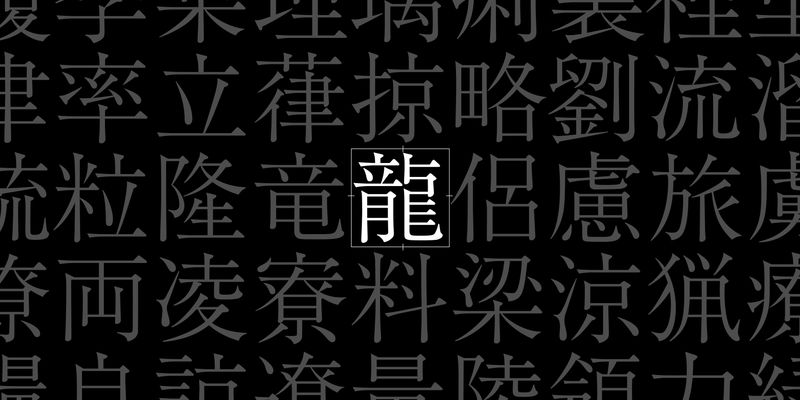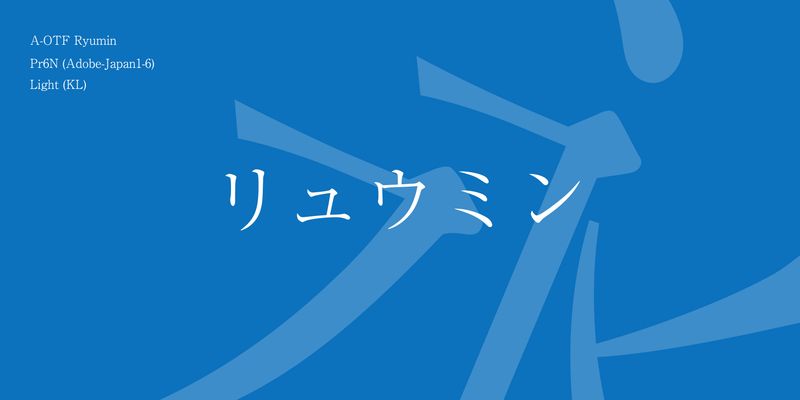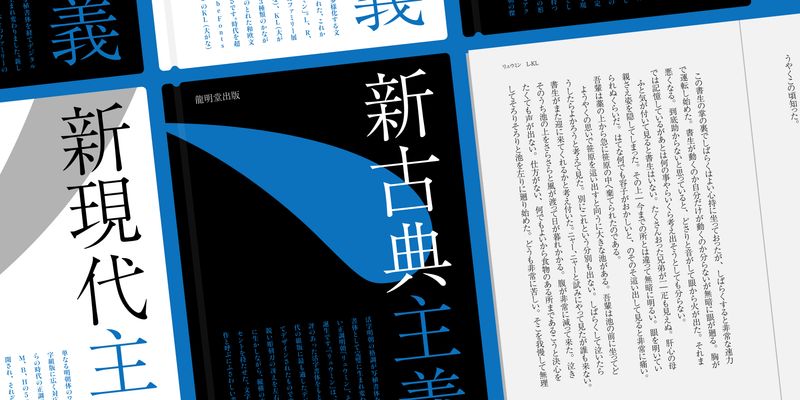
Ryumin es un tipo de letra serif Mincho estándar basado en el tipo Mincho desarrollado por la casa de tipografías Morikawa Ryobundo. Si bien reproduce la nitidez de un cincel en las terminaciones y puntos harai (barrido) izquierdo y derecho, los terminales y el uroko (serif) de los trazos horizontales y verticales tienen una suavidad que le da a la tipografía una sensación amigable. El tipo de letra es bien conocido por su flujo maravillosamente equilibrado y tiene una amplia gama de usos para la composición tipográfica estándar, desde el texto del cuerpo hasta los titulares.